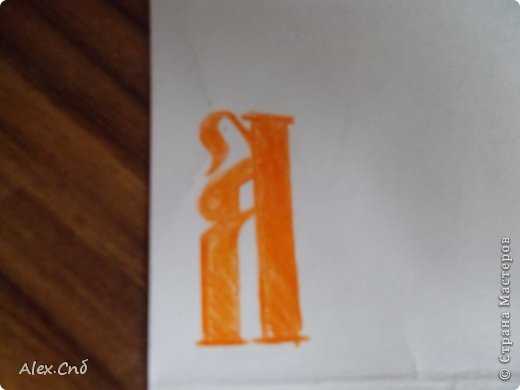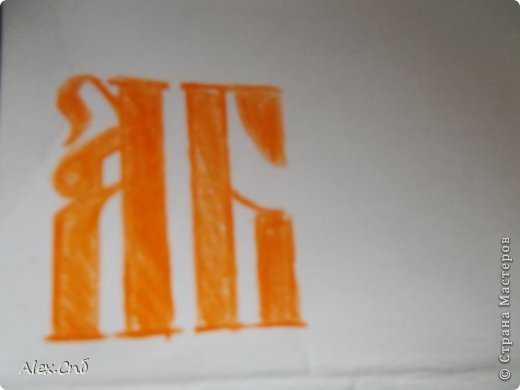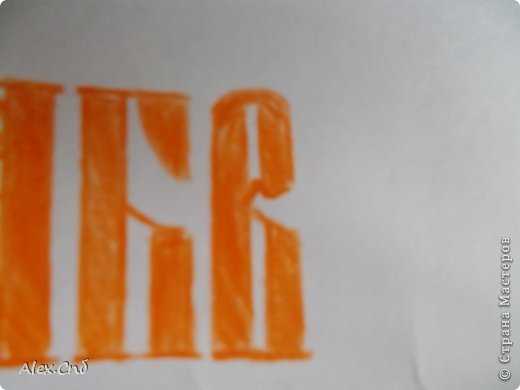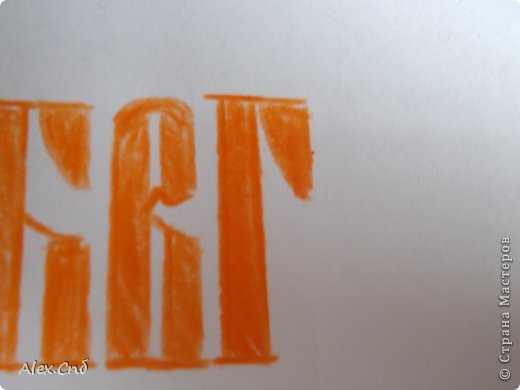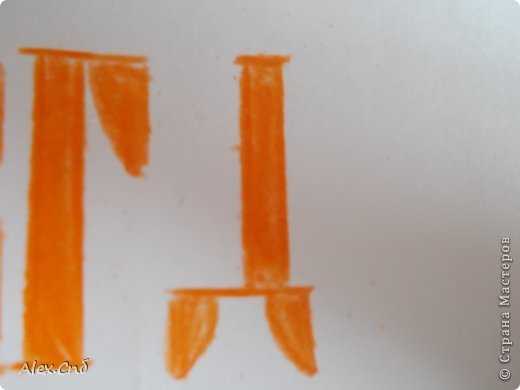
Древнерусские шрифты – Старославянские шрифты | Шрифты онлайн
Творческие люди склонны к поиску новых идей, их реализации и сделают все для расширения возможностей своей работы. Многие пользователи графических и текстовых редакторов осознают, что не каждую задумку можно сформировать за короткий промежуток времени. Большинство сервисов, где они работают, подвергаются критике, потому что в них недостаточно функций и элементов для комфортной работы. К счастью, сейчас эти сервисы позволяют добавлять новые элементы для работы с объектами, увеличивая набор шрифтов, текстур и прочее.
Древнерусский шрифт
В статье мы будем приводить примеры на основе этого шрифта, для наглядности. Дело в том, что на сегодняшний день это один из самых используемых (среди скаченных) шрифтов в русскоязычном сообществе. Рекламщики и оформители нередко применяют древнерусский шрифт для своих проектов. В целом, такой шрифт притягивает взгляды своей неординарностью и связью с отечественной историей. Древнерусский текст больше всего распространен у проектов, связанных с прикладными искусствами.
Стоит учитывать, что не все редакторы поддерживают его, поэтому из множества стилизаций этого шрифта необходимо искать именно те, которые будут адекватно работать в нужной программе. Можно сделать предположение, что у древнерусского шрифта алфавит не должен быть нагружен визуально, поэтому оптимальным вариантом станет поиск упрощенной версии шрифта. Также пользователь должен иметь в виду, что скачанная раскладка будет привязана к русскому алфавиту.
Древнерусский шрифт | Страна Мастеров
Во время учебы наткнулась на проблему: по истории задали сделать старинную газету, а старинного шрифта нигде не найти… Пришлось мудрить и срисовывать с молитвослова. Не зря, конечно, старались, заняли в школе первое место, но нам было очень тяжело. Поэтому я решила сделать МК по древнерусскому шрифту- он полезен и в художественных работах, и в докладах по истории, литературе, русскому языку. Он очень эффектен и сам по себе. Итак, приступим:
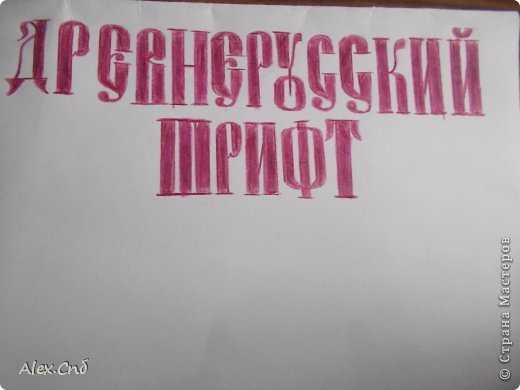
Рисуем букву А: чертим справа длинную ножку, а слева в два раза короче.